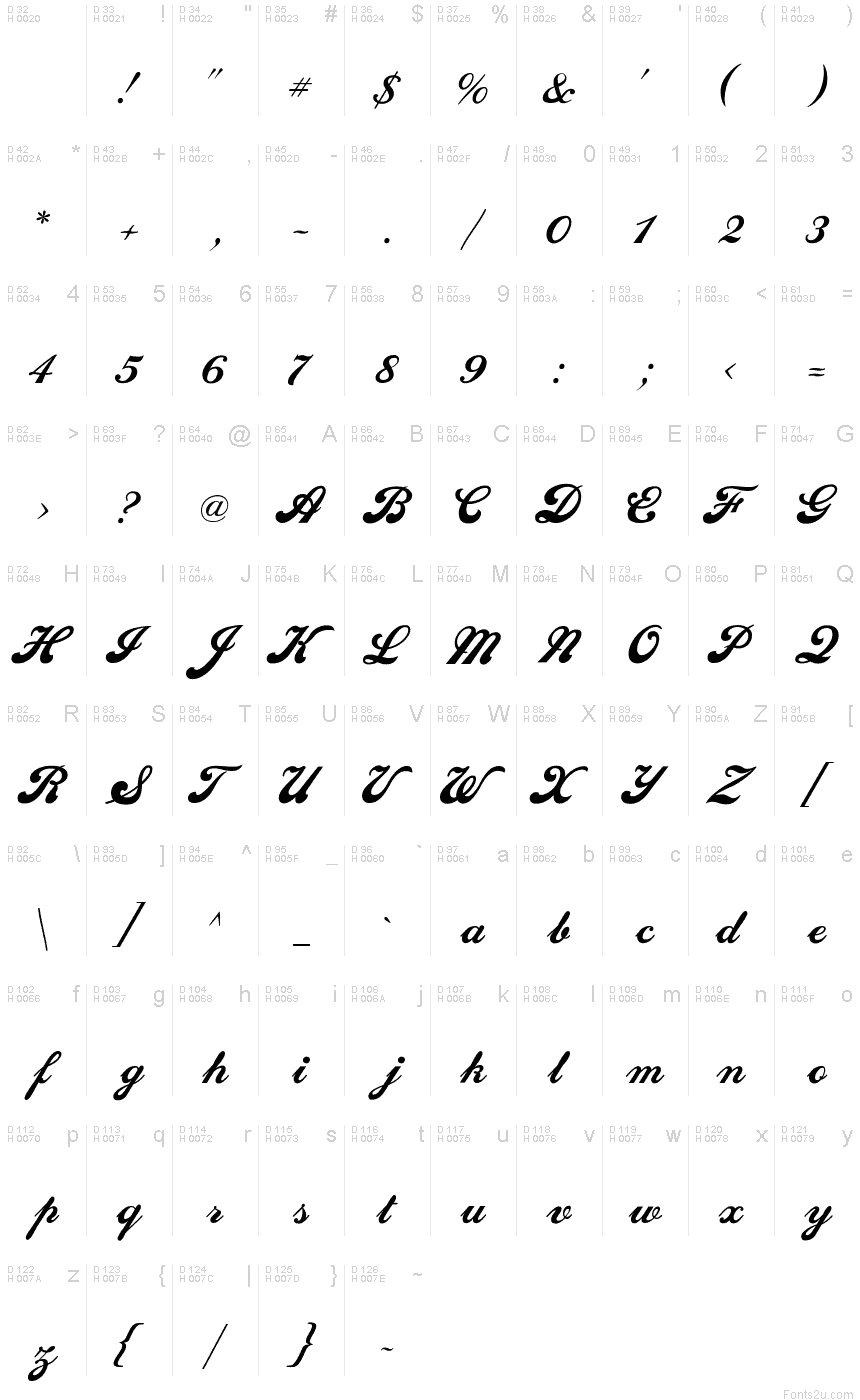
SedonaScriptFLF
Sedona Script FLF di Richard A. Ware è un carattere script calligrafico formale gratuito, composto da ampi anelli e forti tratti che passano da spessi a sottili. Le sue lettere collegate si muovono attraverso curve fluide e generosi fregi.
Come elegante logotipo in stile firma, può dare forma a coordinati nuziali, branding per boutique e confezioni di profumi di lusso con la sicurezza di una scrittura esperta. Il tratto d'ingresso ampio e le giunzioni arrotondate sono particolarmente efficaci per un nome personale o un breve titolo editoriale di moda, dove il lettering può diventare l'elemento decorativo centrale.